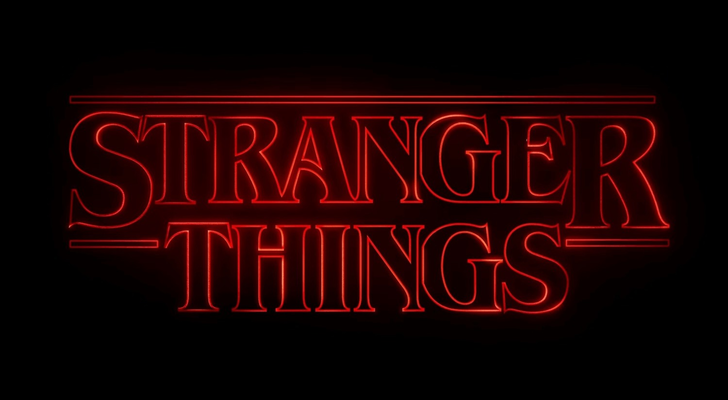
Bevor die Lichter flackern und die Musik einsetzt, erscheint etwas anderes zuerst. Die Buchstaben.
Später in dieser Woche startet die neue Staffel von Stranger Things, und in der gesamten Kreativszene liegt eine vertraute Spannung in der Luft. Nicht nur, weil die Geschichte weitergeht, sondern auch, weil viele darauf warten, wie sich der Titelvorspann erneut langsam und atmosphärisch enthüllt. Das Glühen. Die Körnung. Die Art, wie Typografie uns in eine Welt hineinzieht, noch bevor eine einzige Szene beginnt.
Menschen, die sich mit Gestaltung verbunden fühlen, bemerken solche Augenblicke sofort. Das leise Gleiten eines Wortes. Der weiche Schein um eine Serifenschrift. Die Stille, kurz bevor sich ein Titel endgültig formt. Typografie prägt die Stimmung lange bevor Dialog oder Handlung einsetzen. Sie schafft einen Ton, den kaum ein anderes Gestaltungselement erreicht.
Die Sequenz, die das Interesse an ausdrucksstarker Typografie neu entfachte
Als Stranger Things zum ersten Mal erschien, hob sich sein Vorspann sofort ab. Statt Geschwindigkeit oder Effektüberladenheit setzte er auf bewusste Schlichtheit. Buchstaben wanderten langsam über ein dunkles Feld. Ihr roter Schimmer enthüllte Form um Form. Feine Körnung legte sich wie eine dezente Filmschicht über die Zeichen.
Ein Titel, der ausschließlich aus Buchstaben besteht, wurde zu einem der atmosphärischsten Vorspänne im Fernsehen.
Im Zentrum dieser Sequenz steht ITC Benguiat. Die 1977 von Ed Benguiat entworfene Schrift trägt die Anmutung alter Thriller und Taschenbuchklassiker. Auf dem Bildschirm wirken ihre Proportionen vertraut und doch leicht unheimlich, was ihr eine unmittelbare emotionale Präsenz verleiht.
Originale ITC Benguiat Fototyp-Anzeige
Diese Schrift erschien häufig auf Buchcovern der späten siebziger und achtziger Jahre. Hier einige Beispiele, die zeigen, wie prägend Benguiat für die visuelle Sprache dieser Zeit war:
Dieser zurückhaltende Ansatz erinnerte viele Kreative daran, dass Typografie Spannung, Nostalgie und Atmosphäre mit feiner Präzision vermitteln kann. Mit Staffel 5 kehrt dieses Gefühl nun zurück.
Der Aufstieg typografisch geprägter Vorspänne
Seit dem Erfolg von Stranger Things setzen immer mehr Serien Typografie bewusst ein. Selbst wenn eine Produktion individuelle Schriftzüge verwendet, ist die Absicht klar. Buchstaben werden Teil des erzählten Universums. Sie schaffen Tonalität. Sie prägen Erwartungen.
Dieser Wandel spiegelt eine breitere Entwicklung im Design wider. Menschen greifen zunehmend zu Schriften mit Persönlichkeit und Ausdruck. Zu Typen, die stärker verwurzelt wirken – verwurzelt in Kultur, verbunden mit einer Epoche und geprägt von visuellen Erinnerungen. Viele dieser Formen tragen Anklänge an Printgeschichte, Kino, Subkultur und spekulative Zukunftsvisionen. Manche wirken wie eine leise Form des gotischen Futurismus – vertraut und doch seltsam neu.
Gestalterinnen und Gestalter sprechen häufig darüber, dass sie Typografie suchen, die sich lebendig anfühlt. Etwas mit Textur. Etwas mit Geschichte. Etwas, das die Welt bereichert, die aufgebaut wird. Die Vorstellung, dass ausdrucksstarke Typografie mit der Moderne verschwunden sei, war nie ganz korrekt. Viele Kreative sehnen sich heute nach typografischer Nuance. Es wirkt wie das fehlende Puzzleteil in einer digital geprägten, visuell glatten Zeit.
Warum dieser Moment für alle zählt, die Schriften auswählen
Für die MyFonts Community ist dieser Moment inspirierend. Er zeigt, dass die Wahl einer Schrift immer auch eine emotionale Entscheidung ist. Typografie formt das Gefühl eines Projekts, noch bevor der Inhalt wirkt.
- Eine Serifenschrift mit feiner Spannung kann filmische Atmosphäre schaffen.
- Eine schmale Displayschrift kann den Geist vergangener Jahrzehnte wachrufen.
- Eine klare geometrische Grotesk kann einer Gestaltung Ruhe und Struktur geben.
Typografie gestaltet den Eingang zu einer Geschichte. Sie schafft Erwartung. Sie beeinflusst Stimmung. Sie lenkt den Blick, bevor irgendetwas anderes erscheint.
Dies ist die Botschaft, die Vorspänne wie jener von Stranger Things vermitteln. Buchstaben haben Bedeutung. Und wenn sie bewusst gewählt werden, können sie einen Moment fühlbar und lebendig machen.
Der Moment kurz bevor die Geschichte beginnt
Wenn Sie diese Woche die neue Staffel einschalten, nehmen Sie sich einen Augenblick Zeit, um zu sehen, wie sich der Titel entfaltet. Achten Sie auf das Glühen entlang der Striche. Auf die Stille. Auf den Moment, in dem sich die Buchstaben endgültig formen.
Typografie eröffnet die Bühne. Typografie prägt die Stimmung. Typografie lädt uns ein.
Oft ist es genau diese stille Einladung, die am längsten nachklingt.